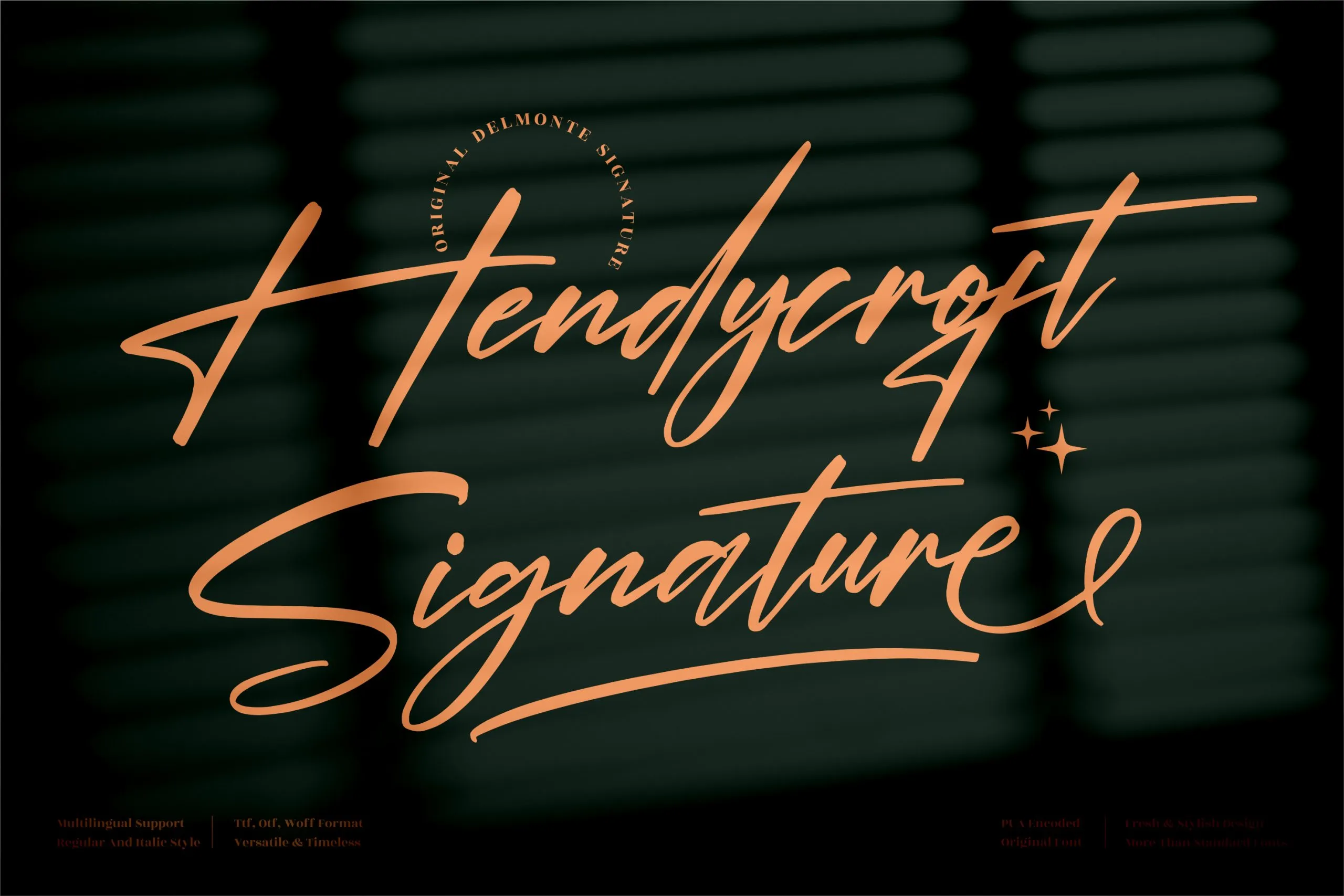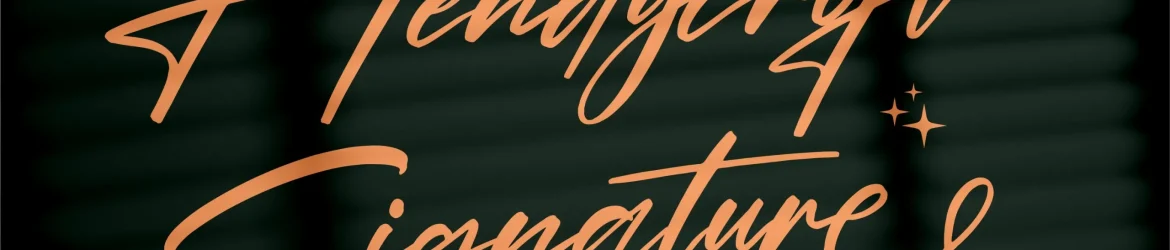
Hendycroft Signature Font – Download Grátis
Esta é uma fonte de firma premium, ideal para um vasto range de projetos que incluem logotipos, campanhas de marca, designs de mobiliário doméstico, embalagens de produtos, tigelas e xícaras, frases, postais, sacolas de compras, camisetas, capas de livro, cartões de nome, convites, cartões de agradecimento, etiquetas, fotografia, marcas e eventos especiais, tudo isso requer um sabor refinado da firma. A Fonte Hendycroft Signature é uma escolha perfeita para suas iniciativas que buscam este toque sofisticado e autêntico. Seja você um designer profissional ou amador, a fonte Hendycroft Signature é ideal tanto para o seu trabalho de casa quanto para os seus projetos empresariais. Seu design elegante e despojado será uma adição incrível a qualquer projeto que deseje dar uma assinatura única e autêntica. Esta fonte não apenas trará um toque diferenciado ao seu design, mas também garantirá um profissionalismo de ponta a zero em tudo o que você fizer com ela.